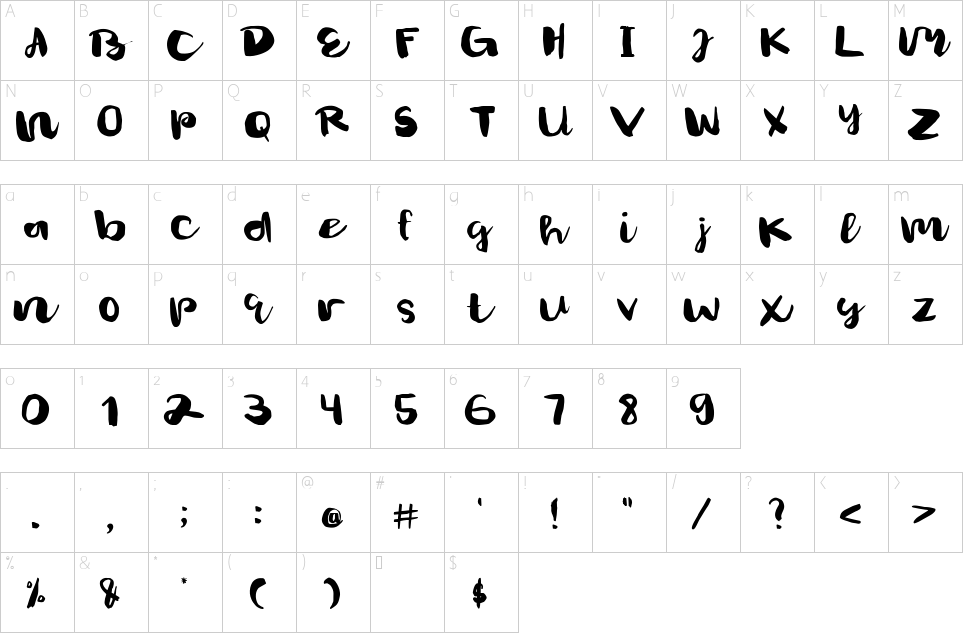
A fonte ‘Gelsson Script Font’ oferece uma experiência única para aqueles que buscam uma letra expressiva e fluida. Desenvolvida pelo designer Suandana Ipandemade, esta fonte é um verdadeiro prazer para os olhos devido à sua delicadeza e elegância. O seu design suave, combinado com detalhes artísticos, cria um resultado que se assemelha a uma caligrafia elaborada. Os criadores pensaram em criar algo único, não apenas um simples recurso gráfico, mas sim um toque de sofisticação e originalidade para qualquer projeto visual. A sua versatilidade permite que seja usada em diversos contextos, desde cartazes de eventos até logotipos de marca, ajudando a destacar seus projetos através da criatividade do design de fontes. Com apenas um download, você pode adicionar uma personalização profissional e elegante às suas criações digitais.